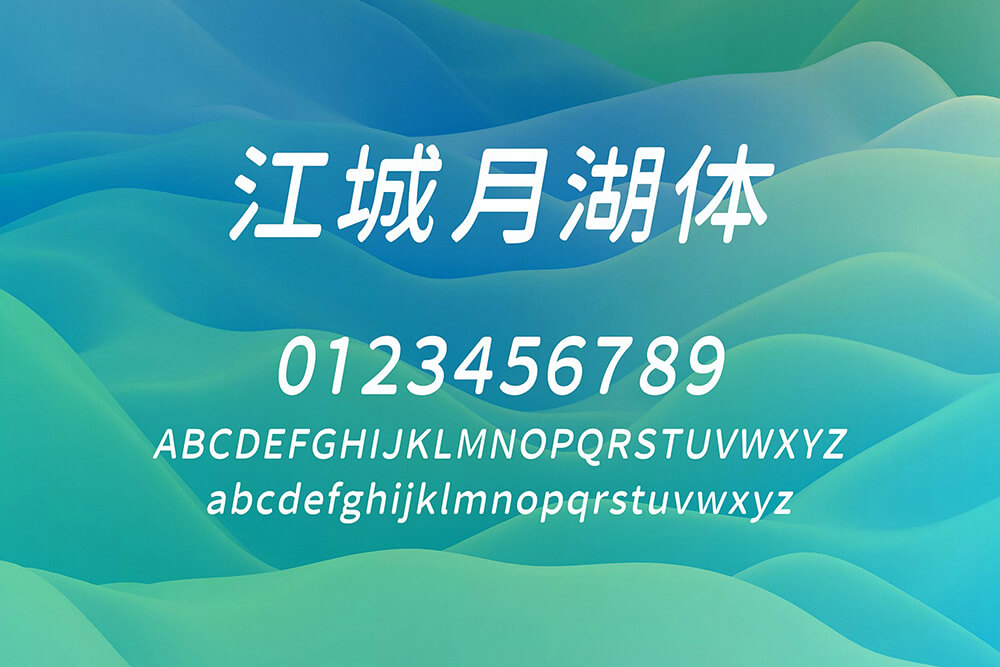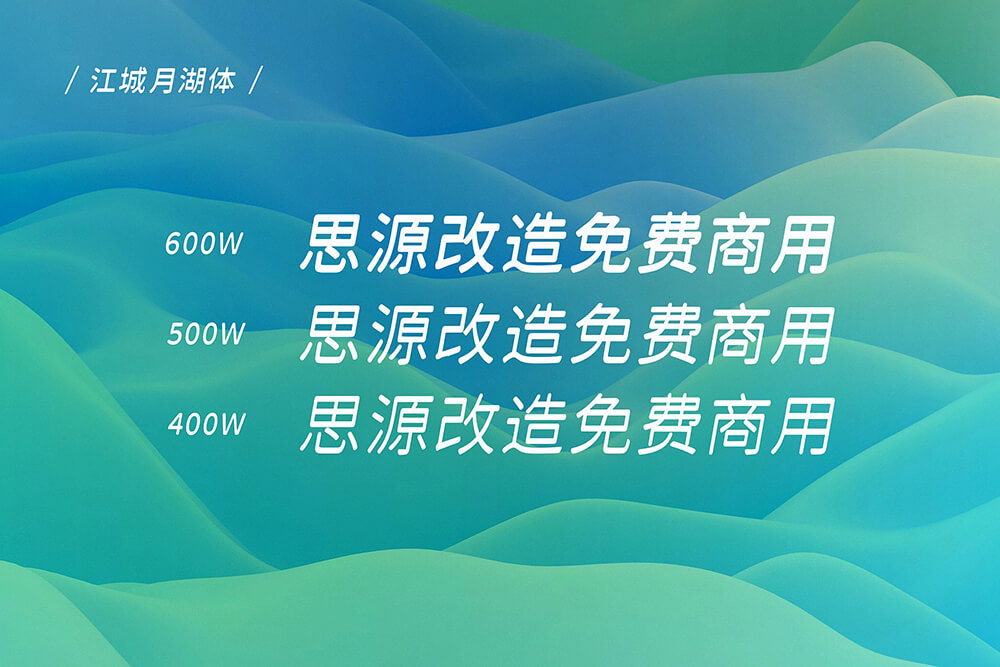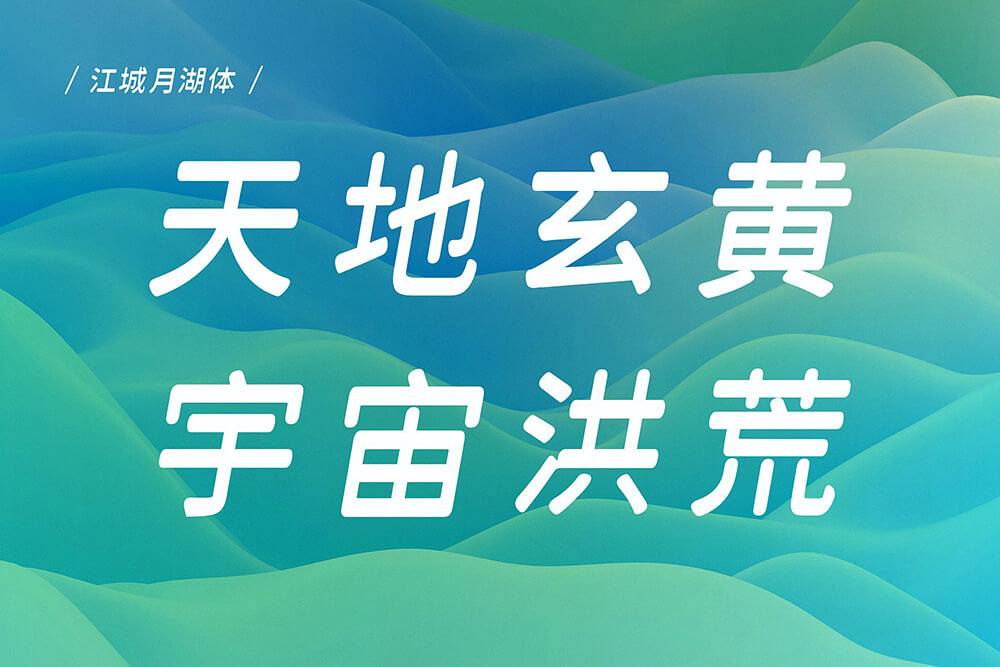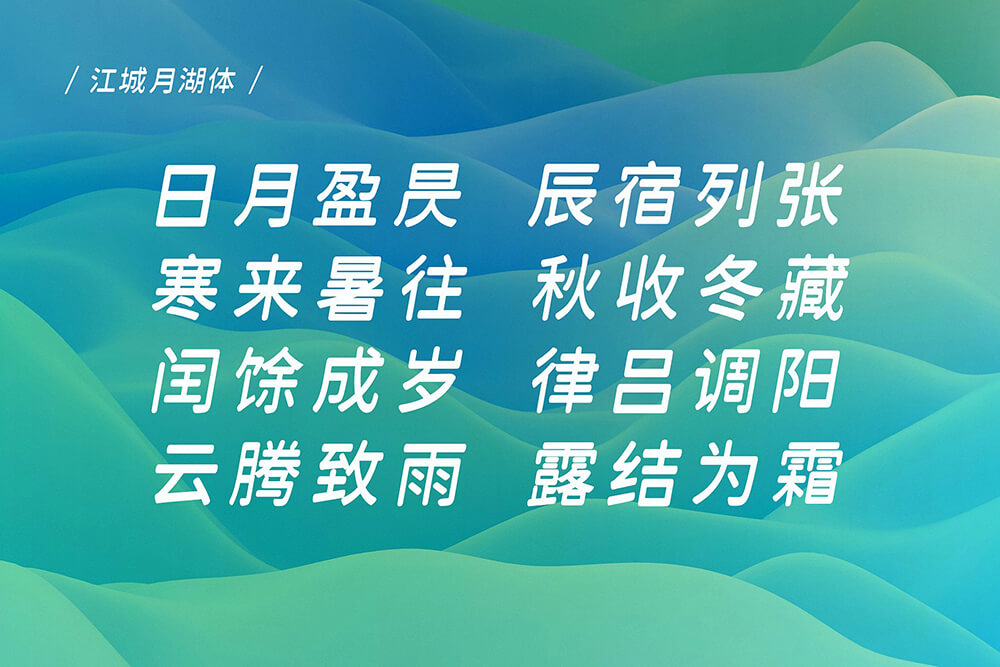
江城月湖体是大神刘鹏发布的江城系列字体又一款力作,江城月湖体基于江城圆体改造而成,和江城知音体相反,是把江城圆体横向增粗处理,纵向减细处理,并把字体进行倾斜10度,而且该字体拥有3个字重。
- 江城月湖体更新了V2.0
- 重新优化了字形改造方式,减少大量毛刺、字宽、字距问题
- 西文字母及数字选用Baloo2改造
Ver 1.6(2020/09/30)
- 修复了网友反馈的字体漂移问题,以及其他字体明显问题
- 增加了符号“·”
- 去掉了数字“1”下面的一横
Ver 1.5(2020/09/28)
- 源字体改选用为狮尾圆体SC,字体更加全面,没有异体字
- 重新调整字体倾斜10度,让坡度更加美观自然
- 增加600W字重,并修复了部分字体空缺和毛刺
- 优化设置了字符范围,让该字体在部分软件中显示区域为中文,更方便国内设计师
- 优化了字体名称信息设置,增加了英文名称,让该字体跨系统Linux系统下名称显示正常
Ver 1.0(2020/06/16)
- 江城月湖体正式发布
江城月湖体也同步更新到V2.0了。另外知音体有张样图错误,我强迫症忍不住想换掉。
江城月湖体V1.6 字体字重值异常:600W 字重,PostScript 字体名(PS名)字段的字重值现为 Demi。建议在后续版本中,修正为 Demi-Bold 或者直接 Bold
我在PS中测试字重显示没有问题,使用正常。
1、修复了网友反馈的字体漂移问题,以及其他字体明显问题
2、增加了符号“·”
2、去年了数字“1”下面的一横
江城月湖体v 1.5 不同字重,有字体漂移: 简体 月 迎间,丽,繁体 网
嗯,我也才看到字体样例里400W500W字重里出现了问题,一次更新修复
大佬能否顺道把数字1下面的一笔除掉,与其它数字放一起不协调
正有此想法,下次更新
竖排文字 沁园春 雪,中间的 圆点 字符缺失。印象中,很多字体都缺失这个字符,或者字符错码。包括 文泉驿的某些字体。常见应用场景: 无序列表 前面的圆点
新增好
1、源字体改选用为狮尾圆体SC,字体更加全面,没有异体字
2、重新调整字体倾斜10度,让坡度更加美观自然
3、增加600W字重,并修复了部分字体空缺和毛刺
4、优化设置了字符范围,让该字体在部分软件中显示区域为中文,更方便国内设计师
5、优化了字体名称信息设置,增加了英文名称,让该字体跨系统Linux系统下名称显示正常
字体名细节待优化:WPS 中选择 江城月湖体,默认使用的是 500W (效果偏粗),而不是默认的 400W
两个字重,建议直接用 regular 和 bold 来标识。更符合字体文件格式规范和流通
这个是用 FontLab VI 加粗的吗?
齦字的400W和500W偏移了